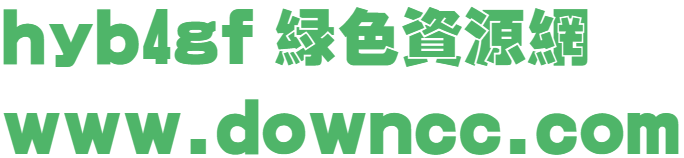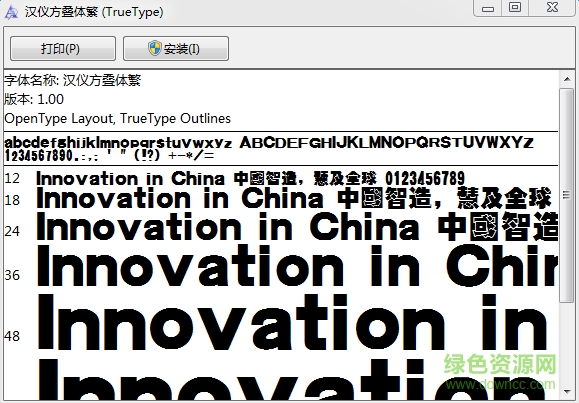
hyb4gf是什么字體?hyb4gf是繁體字體的漢儀方疊體,字面較大,渾厚婉轉(zhuǎn),用作商業(yè)字體和包裝設(shè)計(jì)都不錯(cuò),還有超多漢儀經(jīng)典字體綠色資源網(wǎng)都有,快來免費(fèi)下載吧!
漢儀方疊體繁體是一款很具藝術(shù)效果和設(shè)計(jì)感字體,打出來的字就像是用紙片疊起來的效果,非常好看,繁體版雖然在設(shè)計(jì)中用途不如簡(jiǎn)體版廣泛,但效果還是很不錯(cuò)的哦!